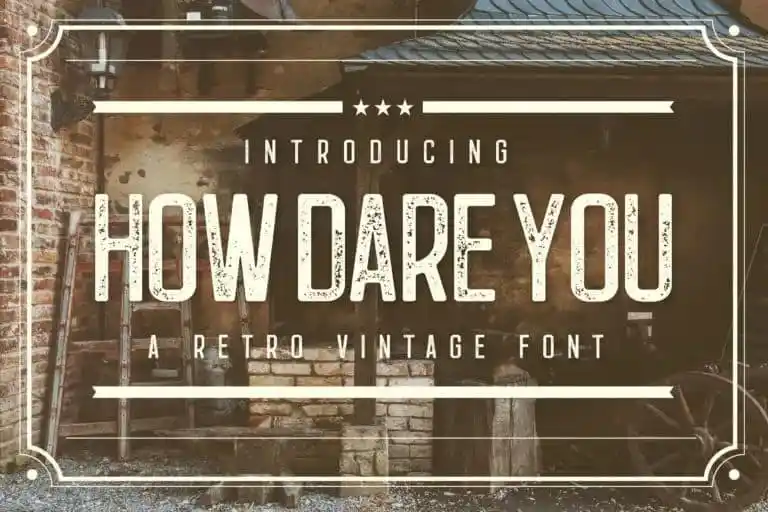
How Dare You Display Font – Download Grátis
A How Dare You Display Font é uma fonte totalmente em letras maiúsculas com caracteres grandes e pequenos únicos. Ela foi criada por Type Factory para projetos relacionados ao esporte, mas agora pode ser usada em diversos tipos de projetos, desde criar slogans até logos e capas de revistas. O design retro-vintage dessa fonte a torna perfeita para qualquer tipo de projeto que exija uma aparição vintage e ousada. Com seu estilo atrevido, How Dare You Display Font é ideal para designers que buscam dar um toque único em suas criações, seja na moda ou no lifestyle. Perfeito tanto para usar nas letras grandes como nos subtítulos, essa fonte destaca-se pelo seu design simplesmente incomum. Os criadores de Type Factory não apenas compartilharam sua criação com a comunidade 99designs, mas também fizeram dela um recurso versátil e divertido para designers gráficos. Seja você um entusiasta da moda, um apaixonado por esportes ou alguém que adora revistas, essa fonte certamente tem algo a oferecer.